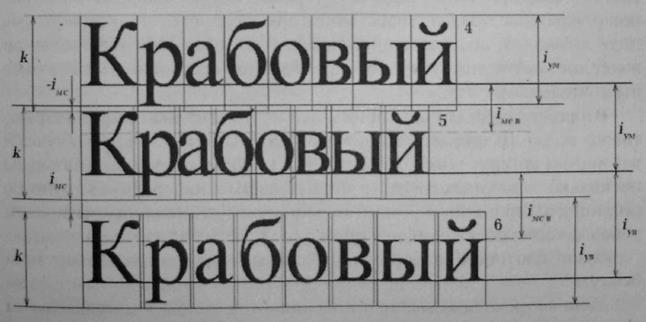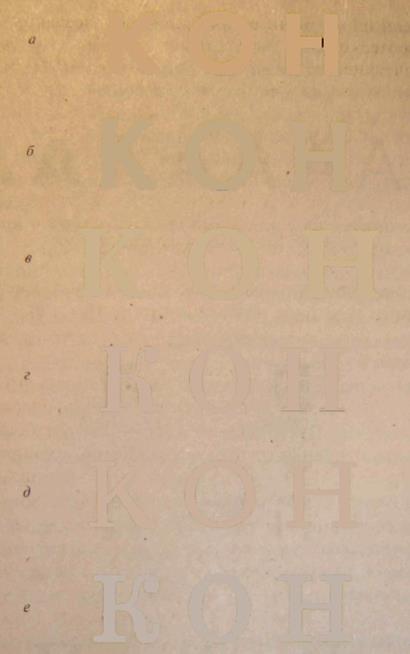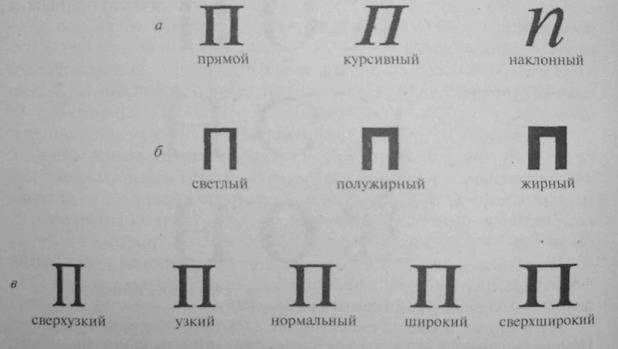
Шрифты и их параметры
Шрифт — это средство графической организации текстового доку­мента.
Прежде чем приступить к описанию шрифтов, рассмотрим тради­ционно используемую систему измерений, поскольку параметры шрифтов и набора описываются в типографских единицах измерения.
Система измерений. Наряду с метрической системой для описания параметров текстового набора традиционно используется типографская система измерений, разработанная в 1785 г. француз­ским типографом Дидо. В основу типографской системы был положен дюйм, во Франции равный 27,077 мм, так как метрическая система к тому времени еще не была принята. Типографская система применя­лась и в настоящее время все еще ограниченно применяется для описа­ния параметров набора (размеры шрифта, форматы строк, полос и т.д.) в нормативных материалах и стандартах России.
Основной единицей типографской системы измерения является типографский пункт (п.), равный 1/п дюйма (1 п. = 0,376065 мм» «0,376 мм). Более крупные единицы: 1 цицеро = 12 п., 1 кв. (квадрат) = = 48 п.
В США, Великобритании и некоторых других странах была приня­та аналогичная первой англо-американская типографская система, в основу которой также положен дюйм (inch, in), равный в Великобрита­нии 25,4 мм, В англо-американской системе 1 пункт (пт, point, pt) & 1/72,27 дюйма ~ 0,3514 мм. Более крупной единицей является пика (пайка, pica): 1 пика = 12 пт.
Для последних лет было характерным широкое внедрение компью­терной техники, в том числе в издательско-полиграфические процес­сы, и поступление соответствующих программных продуктов из анг­лоязычных стран. В указанных программных продуктах для описания параметров шрифтов и шрифтового набора используется англо-амери­канская система.
Однако для унификации шкал и расчетов используют целочислен­ные соотношения: 1 пункт (пт, point, pt) = 1/72 дюйма» 0,353 мм, так называемый PostScript-пункт,
Поскольку в государственных стандартах РФ параметры книжно-журнальной продукции нормируются в типографской системе (Дидо), при пользовании такими программами следует внимательно относить­ся к установке параметров шрифтового набора для соблюдения суще­ствующих санитарно-гигиенических требований к набору и оформле­нию изданий.
Для нормативного набора с соблюдением существующих требова­ний следует перед началом набора (верстки) установить параметры шрифта, руководствуясь вышеприведенными соотношениями.
Кроме указанных единиц измерения, в компьютерном наборе ис­пользуется относительная единица — шпация, характеризующая гори­зонтальный размер шрифта. Круглая шпация равна кеглю шрифта или примерно ширине прописной буквы А, полукруглая шпация составляет 0,5 кегля или ширину прописной буквы N, тонкая шпация — 0,25 кегля или ширину строчной буквы t(f). Классические правила на­бора регламентируют нормативные отбивки в тексте в пунктах без ука­зания на кегль шрифта. Однако для лучшего восприятия текста важны не абсолютные расстояния, а их отношение к величине символов (кег­лю). Поэтому использование относительной единицы, а также шпации как элемента набора — постоянного пробела — делает отбивки про­порциональными кеглю.
Понятие и параметры шрифта. Рассматривая процесс обработки текстовой информации как область информационных технологий, шрифтом называют совокупность (систему) знаков набора, предназначенных для визуализации текстовой информации на всех этапах ее обработки.
В типографике существенным является признак, в соответствии с которым указанная совокупность знаков набора может быть названа шрифтом, а именно: рисунки символов базируются на некоторой об­щей для всех, единой графической основе (концепции рисунка).
Шрифт как знаковая система включает строчные или прописные буквы одного или нескольких алфавитов с относящимися к ним знака­ми препинания, лигатуры, логотипы, цифры, специальные символы и оформительские элементы.
Изображение шрифтового знака называют печатным очком или оч­ком, что связано с исторической традицией именовать, таким образом, печатающий элемент литеры. Оно формируется из основных и соеди­нительных элементов (рис. 16.5). Основными являются вертикальные штрихи, соединительными — горизонтальные, наклонные или округ­ленные штрихи, которые у большинства шрифтов тоньше основных. Соотношение ширины са основных и — сб соединительных штрихов — контрастность К шрифта:
К= са / сб.
Расстояния с между основными штрихами называются внутрисимвольными (внутрибуквенными) просветами.
Рис. 16.5. Строение символов шрифта:
1 - основной шрих (са);
2 - соединительный штрих (сб);
3 - засечка (сериф);
4 - верхний выносной элемент;
5 - нижний выносной элемент;
6 - наплыв;
7 - внутрисимвольный (внутрибуквенный) просвет с;
8 - овал;
9 - полуовал;